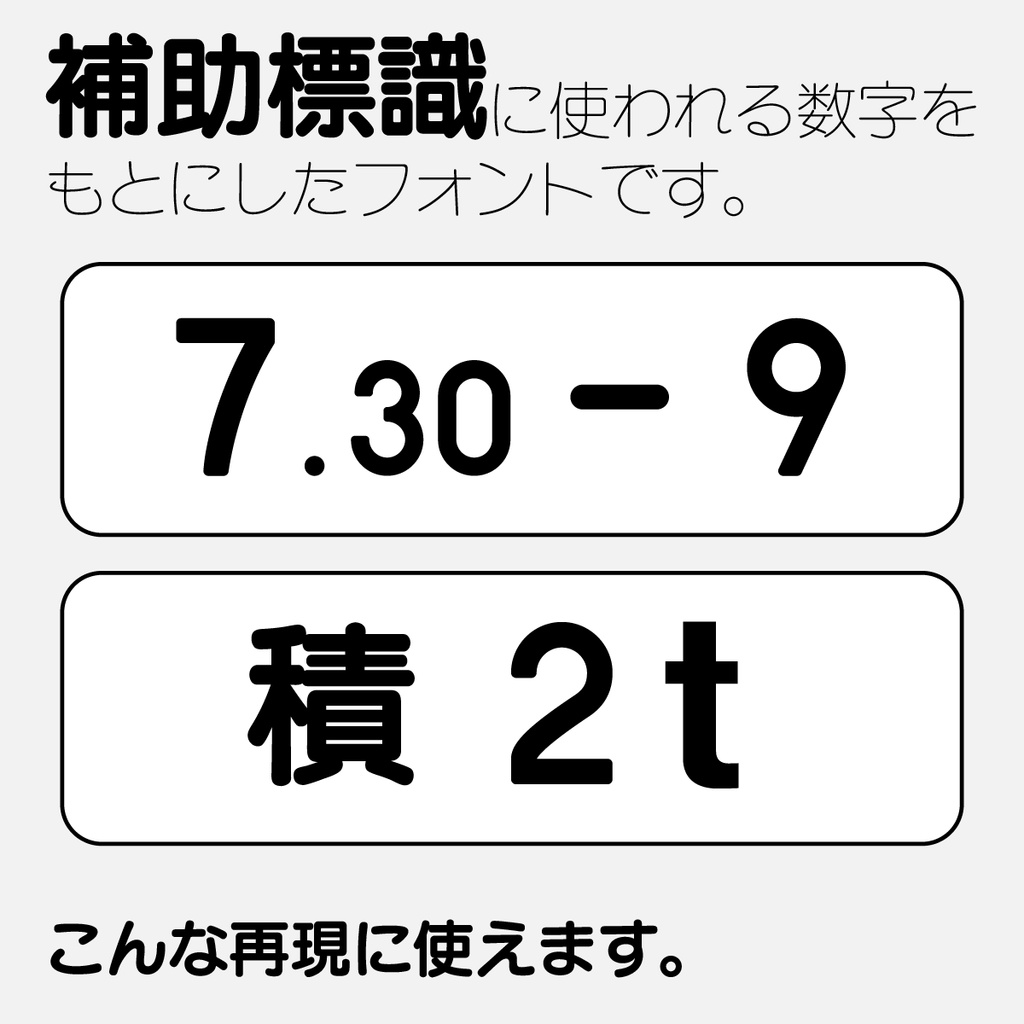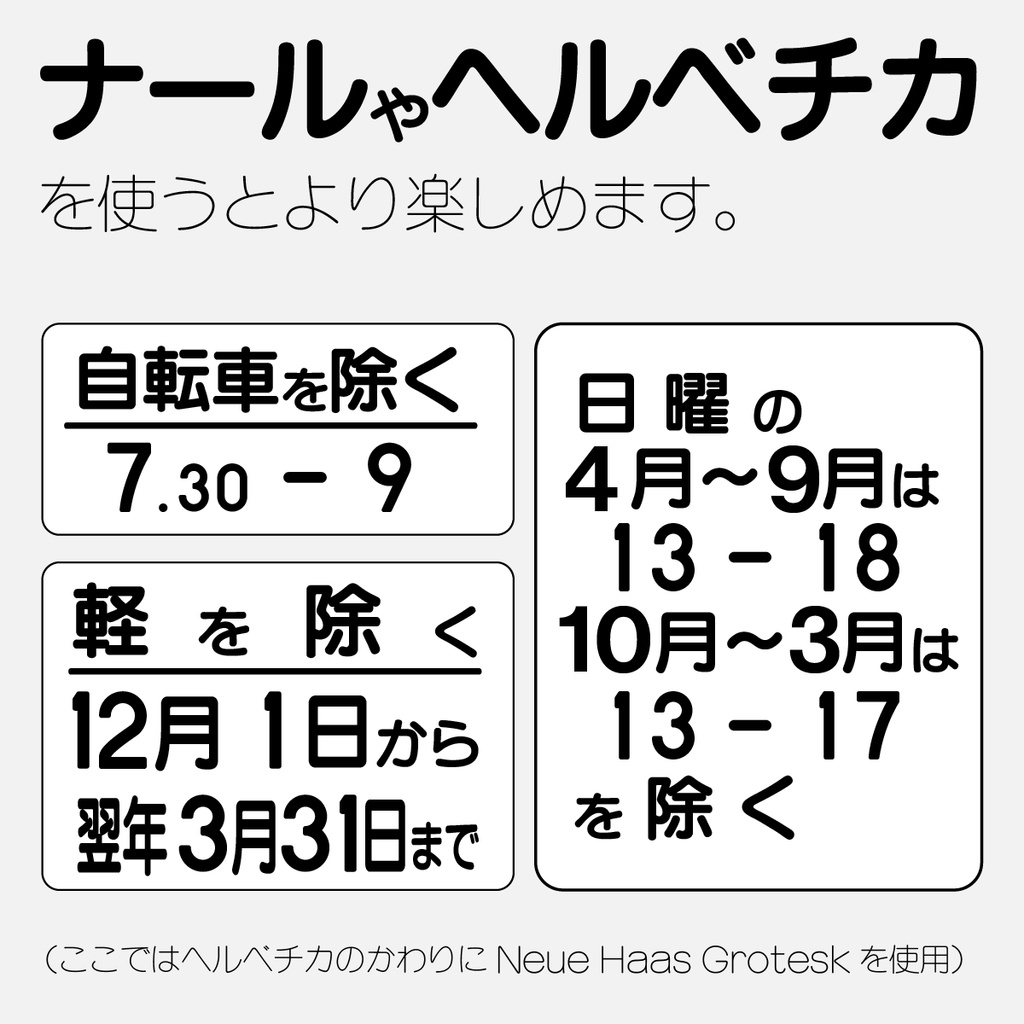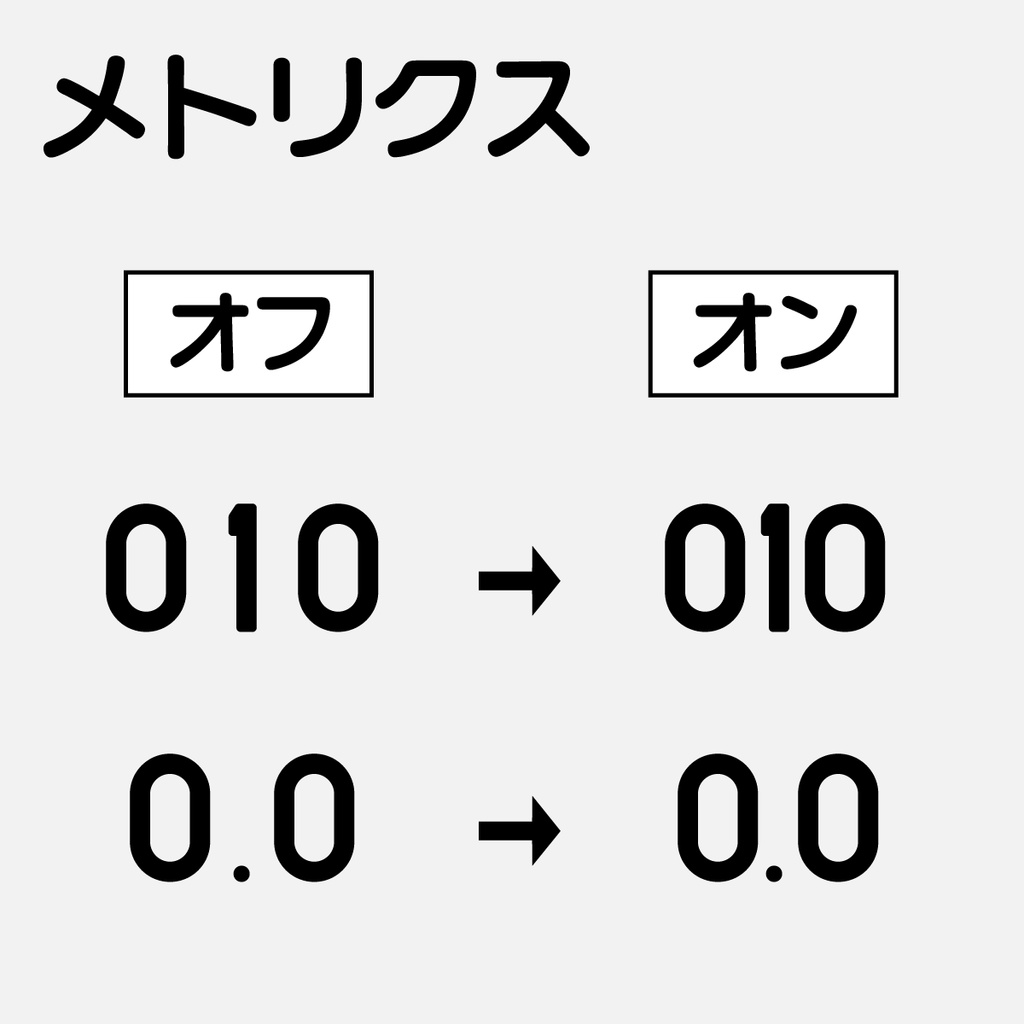
フリーフォント 補助標識用数字書体「ほじょナンバー」
【説明】 道路標識の中でも補助標識に使われている数字書体を元に制作したフォントです。実際は標識によって細かな違いがありますが独自に解釈しています。 本標識(速度制限など)に使われる数字書体と似ていますが、字形が異なり、また角に丸みをつける処理をしています。 補助標識用とは言っていますが、可読性が高い為、数字を使う場面で有効かもしれません。 さゆぬ氏による標識フォント「Nu みちしるべ」にインスパイアされ、標識に使われる写研「ナール」OTF化にも伴い作ったフォントです。 【仕様】 このフォントはOTFです。 等幅の数字「1234567890」、ハイフン「-」、等幅の半分のピリオド「.」が収録されています。(等幅の半分の空白も収録) また「1」と「.」にはプロポーショナルメトリクスがあり、オンにすると、他の数字と同じアキ間隔に変わります。 また、補助標識は日本語にナール、数字にヘルベチカが使われていることもある為、併用するとよりそれらしくなります。 (イラレでのナール併用を視野に入れてはいますが、同じテキスト内ではアキが目立ちます。それぞれ別にテキストオブジェクトを作り、文字サイズや間隔を合わせると良いです。実際の補助標識でも文字間隔が物によってバラバラです。好きな配置でデザインしましょう。) 【利用規約】 "SIL Open Font License"による 【更新履歴】 ver 1.0 公開